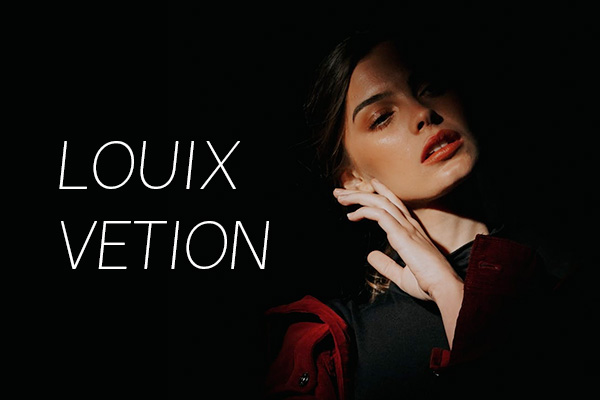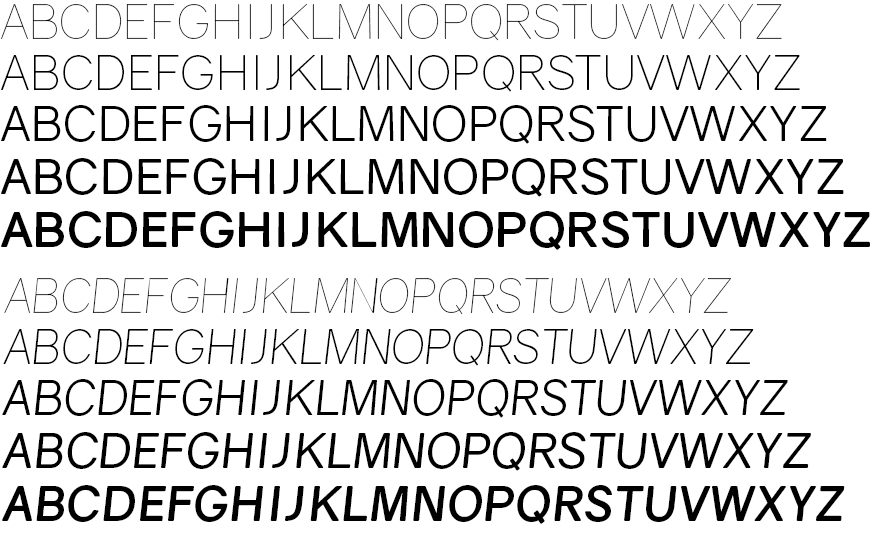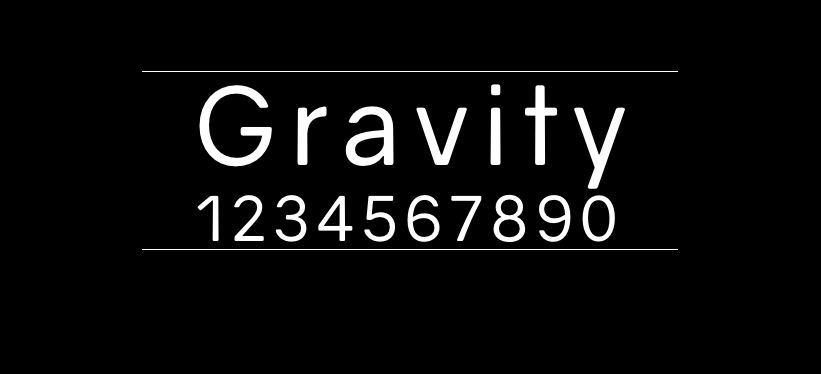
Gravity
Gravity字体介绍
Gravity是国外的设计师Vincenzo Vuono创作的第一款字体,Gravity来自一次印刷实验,源自对作者加深对这一学科知识的渴望。Gravity还是一种新的无衬线几何无衬线字体,设计有平衡和较大的计数器。Gravity字体使用“重力”作为字体的独特,功能和美学特征。
Gravity拥有5个字重,并且包含了斜体,共10种样式,是一款不可多得的免费英文字体,喜欢的赶快下载吧!该字体由热心网友“卡路里滚蛋吧”(QQ850665439)提供信息,感谢他的支持!
Gravity字体应用示例